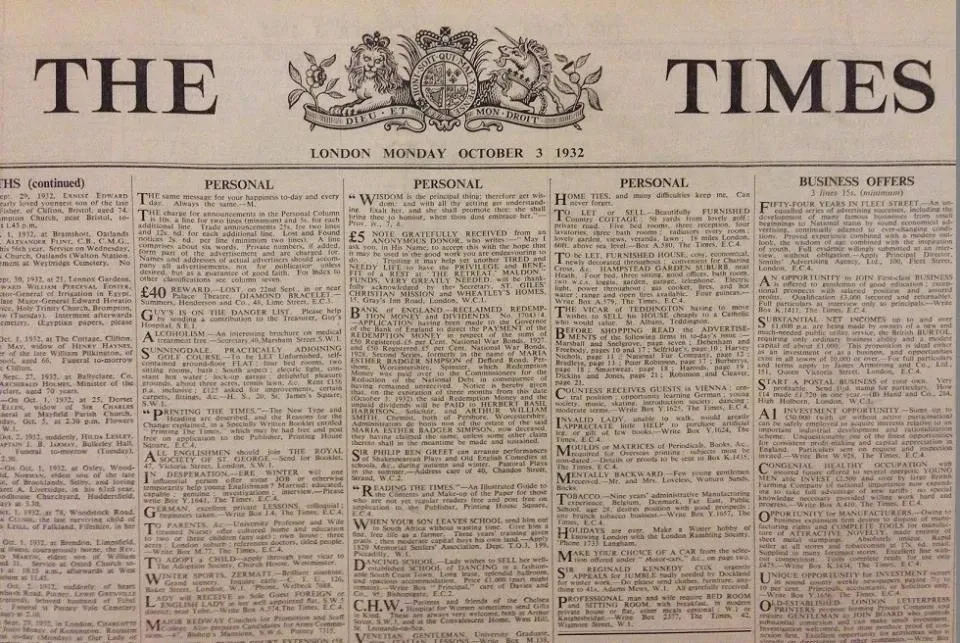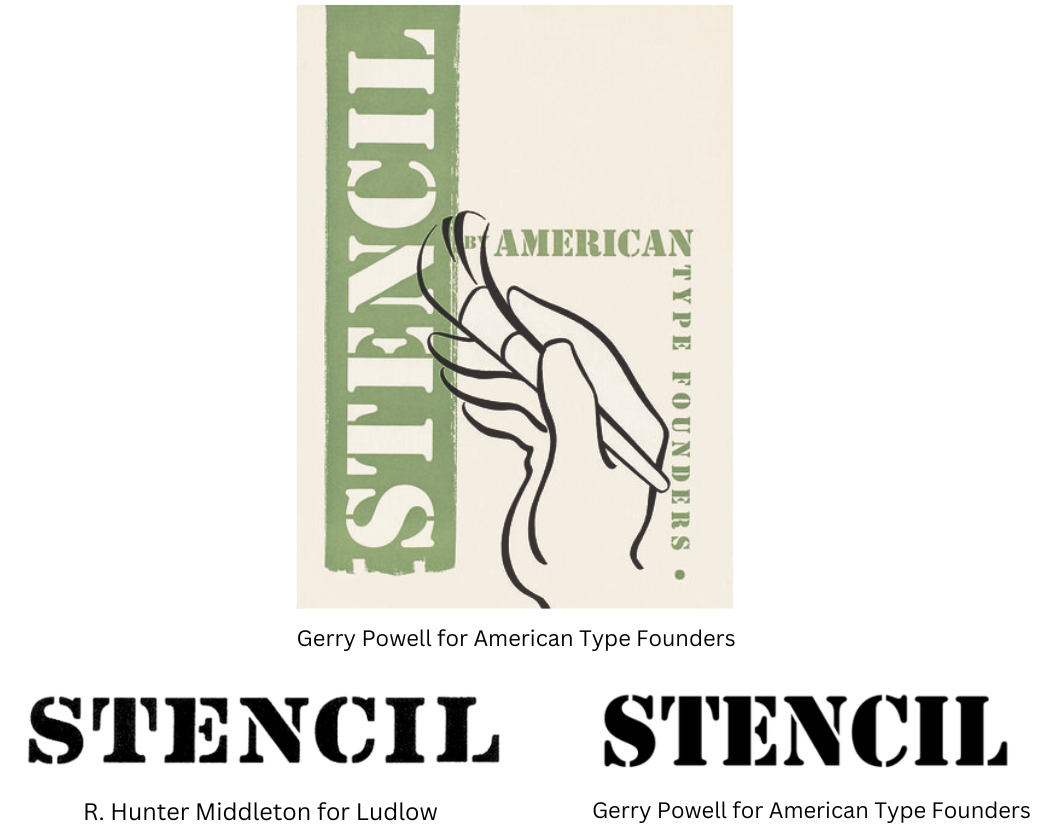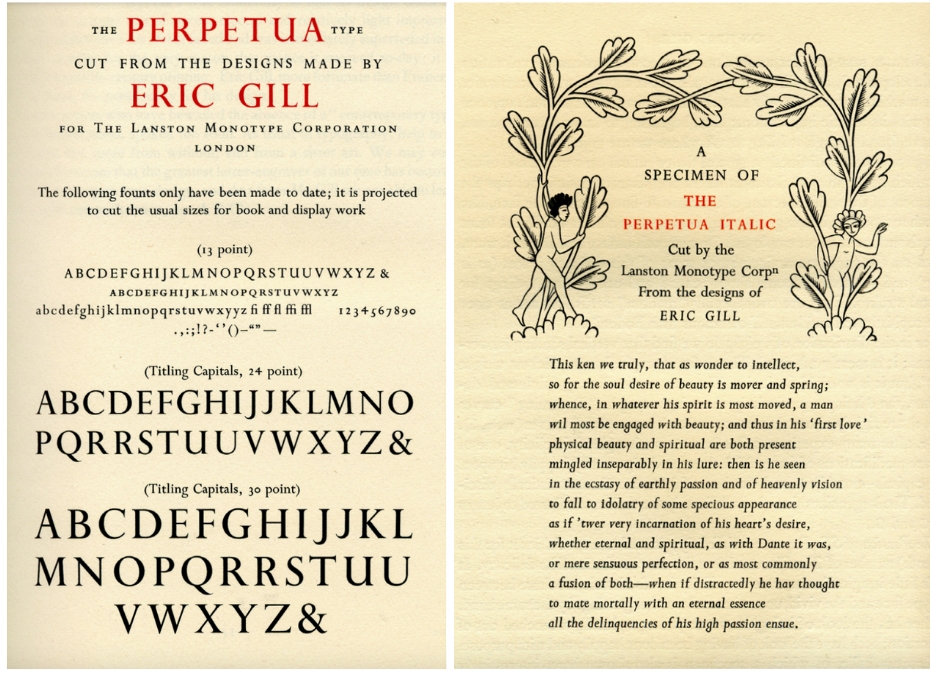
🤓 Типографика 1930-х: Шрифты, меняющие мир
Когда мы думаем о дизайне, часто нам на ум приходят цвета, формы, может быть, даже логотипы. Но заметьте, шрифты – это магия, которую чаще всего воспринимаем как данность. Но как же здорово, что всё это началось ещё в 1930-х!
Эта эпоха стать основополагающей как для типографики, так и для всей индустрии дизайна в целом. Время мировых сотрясений и стремительных рекламных бумаг, когда каждая буква практически кричала: «Смотрите на меня!».
Первая волна типографической революции
Вспоминаю свои студенческие годы, когда зачитывался историями о шрифтах – это настолько захватывающе! Можем начать с Times New Roman –, который, можно сказать, стал будто бы символом современности с его засечками. Разработанный Стэнли Моррисоном, этот шрифт пришёл на выручку многим издателям, поскольку он не только выглядел шикарно, но и решал проблему нехватки места на страницах. «Кто не любит много букв на одной странице, верно?» 😅
Теперь давайте переместимся к 1937 году, когда родился Peignot. Этот шрифт словно объединил невидимые нити ар-деко и экспериментальных форм. В Европе было невозможно не заметить его влияние. Он словно коктейль, смесь стилизованных визуальных решений и передовых идей. Вот это да!
Геометрическая элегантность
Попрошу заметить! Memphis – точно шрифт, который стал символом современного геометрического дизайна. Простота линий и уверенные формы – он будто призывает нас: «Смотрите на мир легко и просто!» Его легко украшают любой проект, и этот шрифт как бы говорит: «Ничего лишнего, только стиль».
А что насчёт классики? Albertus – пришёл в мир дизайна из далёких 1930-х. Он возник в руках Бертольда Вольпе и быстро завоевал популярность на обложках книг и через рекламные материалы. Этот шрифт – словно швейцарский нож: всегда под рукой и к большинству проектов подходит. 🔥
Возвращение к истокам
Вспоминаю, как в университете мы всё время прорывались к созданию уникального euclid шрифта, который изначально представлял собой работу Алвина Ластига. Через все эти годы, он не потерял актуальности, а, наоборот, стал востребованным в современном дизайне. Это замечательный пример того, как шрифты эволюционируют, перепроживая моменты своего существования.
А теперь в сторону индустриального романтизма! Stencil – это американский шрифт, обросший мифами и ассоциациями с военной темой. Кажется, его шаги, как пулемётная очередь, создали ощущение свободы в искусственном мире.
Серые носители типографики
Perpetua, взлетающий шрифт, созданный Эриком Гиллом, – это настоящая веха в развитии serif-шрифтов. После него мир дизайна уже никогда не был прежним. С его помощью можно создать атмосферу таинственного шика, не правда ли?
И не забудем про Rockwell, который стал более чем просто шрифтом – он стал модой. Его слепая чёткость и выразительность в заголовках говорят нам: «Я здесь, чтобы быть заметным!»
Как наследие влияет на наше восприятие
Подводя итог всему сказанному, шрифты 1930-х – это не просто красивые символы. Это отражение характера времени, в котором они были созданы. Это впрямую напоминает о том, как важна каждая деталь в дизайне. 😍
Шрифты продолжают жить в нас, они обнимают и формируют наш взгляд на мир графического дизайна. Поэтому стоит ли нам забывать об этом историческом наследии? Эй, самое время задуматься, какие шрифты помогут выразить вашу уникальность в текущем мире!